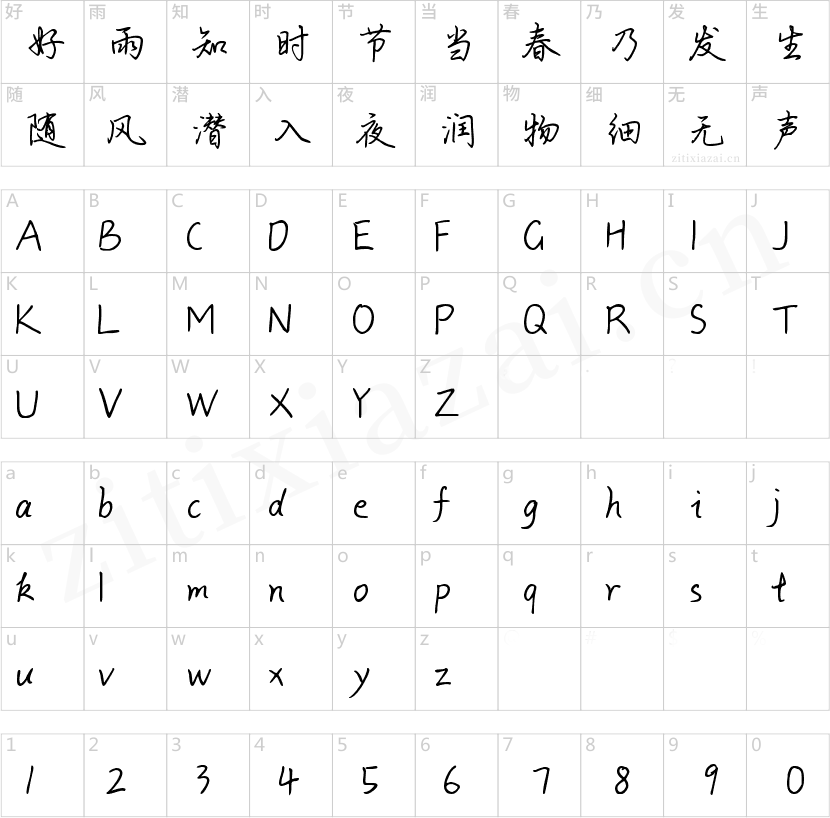
Aa花语紫罗兰永恒
Aa花语紫罗兰永恒字体
Aa花语紫罗兰永恒是一款非常具有艺术性的字体,它的设计灵感来源于对古典艺术的研究,同时又融入了现代字体设计的元素。字形优美,笔画粗细变化自然,给人以大气、典雅的感觉。Aa花语紫罗兰永恒是一款既传统又现代的字体,它的设计充满艺术感,美观大方,实用性也非常强。无论是对于设计师还是对于普通读者来说,都是一种非常不错的字体选择。Aa花语紫罗兰永恒适合用于具有艺术感的场合,比如海报、宣传单张、书籍封面等。由于其字形流畅且具有动态感,也适合用于大量的文本排版,如报纸、杂志等。